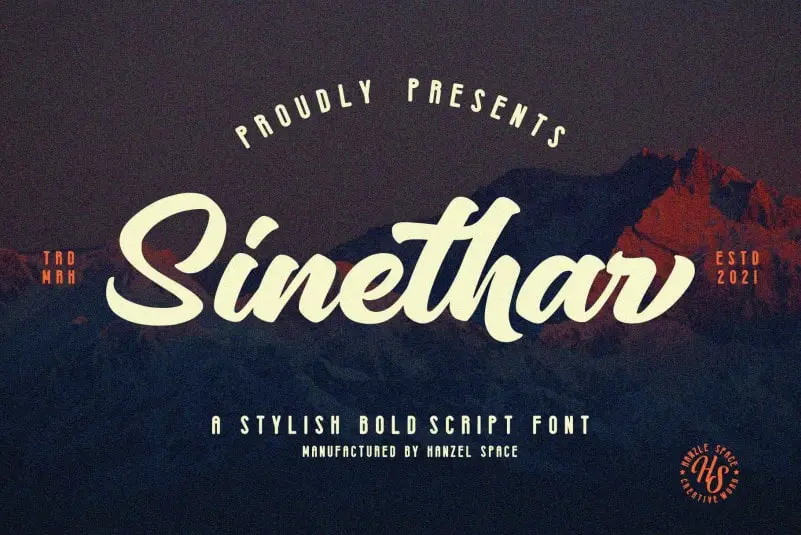
Sinethar Bold Script Font – Download Grátis
Sinethar Bold Script é uma fonte elegante inspirada nas tipografias clássicas do século 19 mas adaptadas para a era contemporânea. Este conjunto sofisticado e encantador combina a perfeição dos tempos passados com o charme moderno, resultando num design que se destaca e é particularmente indicado para criar ilusões de escrita à mão livre. Ideal para logomarcas, citações escritas a mão, embalagens de produtos, cabeçalhos, posters, materiais de merchandising, mídias sociais e cartões de cumprimentos, esta fonte oferece uma série de benefícios extra através dos swashes. Engane-se sobre o conceito de elegância e encanto com Sinethar Bold Script. Acesse agora para experimentá-la em seu próximo projeto!